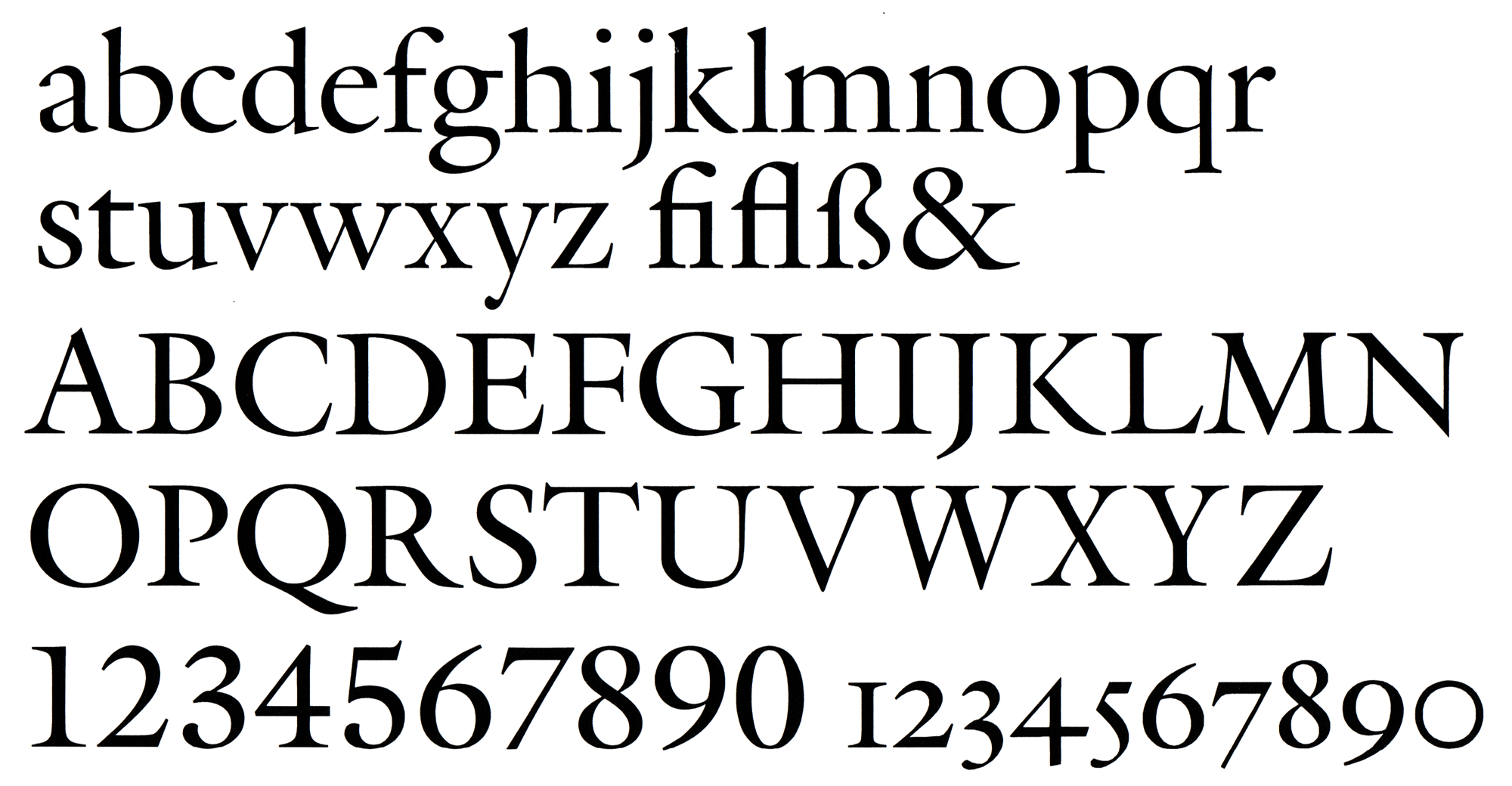
- 1978
- Antiqua humanistisch
Als Vorlage für die Galliard von Matthew Carter dienten Schriften, die Robert Granjon Mitte des 16. Jahrhunderts schuf. Für die Antiqua war dies die von Plantin in Antwerpen 1567 angeschaffte Gros Cicero, für die Kursive die 1570 im Auftrag Plantins geschnittene Ascendonica Cursiue (20 Punkt Didot). Granjons Gros Cicero fällt insbesondere durch ihre für die Zeit vergleichsweise große x-Höhe auf. Die Kursive gibt sich äußerst lebendig und charakterstark. Außerdem besitzt sie auffällige Schwungbuchstaben und Ligaturen, die sich zumindest teilweise in der ITC Galliard wiederfinden. Die Bezeichnung Galliard geht auf die von Granjon geschnittene 8-Punkt-Antiqua zurück, die dieser nach einem Volkstanz »La Gaillarde« benannt hatte.
Die Veröffentlichung der Schrift zog sich lange hin, denn ihre Entwicklung fiel im Sinne der Schrifttechnik auf turbulente Zeiten. Die Entwürfe entstanden zunächst für das Linofilm-System, das eine Einteilung der Buchstabenbreiten auf 18 Einheiten verlangte. Nach zwei Versuchen, die Feinheiten der Schrift in diesem System akzeptabel wiederzugeben, wurde das Projekt zunächst fallengelassen. Mit dem später erschienenen Linofilm-Quick-System war die technische Ausgangslage besser, jedoch war das System an sich kein Verkaufsschlager, sodass es auch hier zu keiner Veröffentlichung der Galliard kam. Erst mit dem Linotype-VIP-System mit 54 Einheiten wurde das Projekt schließlich realisiert und die Schrift erschien 1978 in vier aufrechten und kursiven Schnitten.
Drei Jahre später übernahm ITC die Rechte an der Schrift und verhalf ihr weltweit zu einer großen Verbreitung. Durch die im PostScript-Format üblichen 8-Bit-Zeichensätze war der Zeichenumfang zunächst gegenüber den Originalentwürfen geschrumpft. Jedoch gibt es heute wieder Pro-Versionen mit größerem Zeichensatz inklusive verschiedener Ziffernsets, Ligaturen und Schmuckbuchstaben.
Für Lesetexte am Bildschirm kam 2013 noch eine von Carl Crossgrove überarbeitete eText-Version in vier Schnitten heraus.